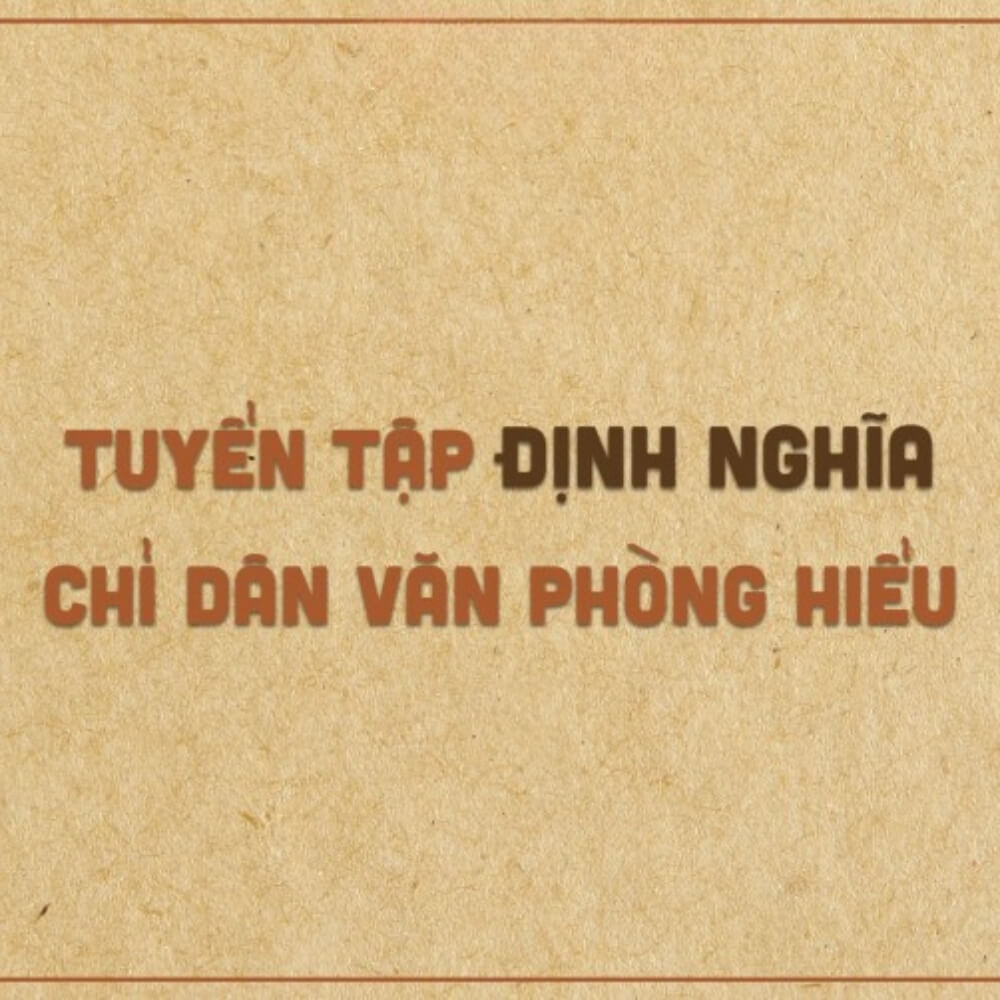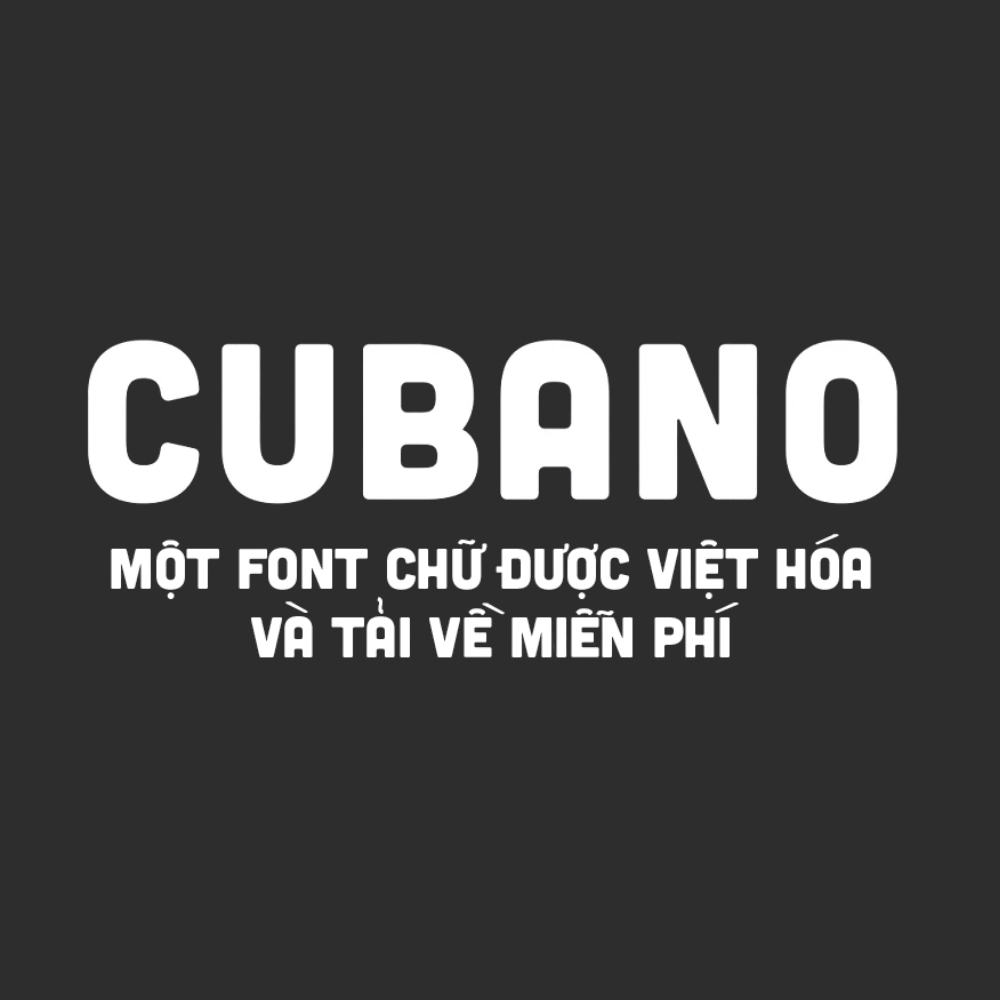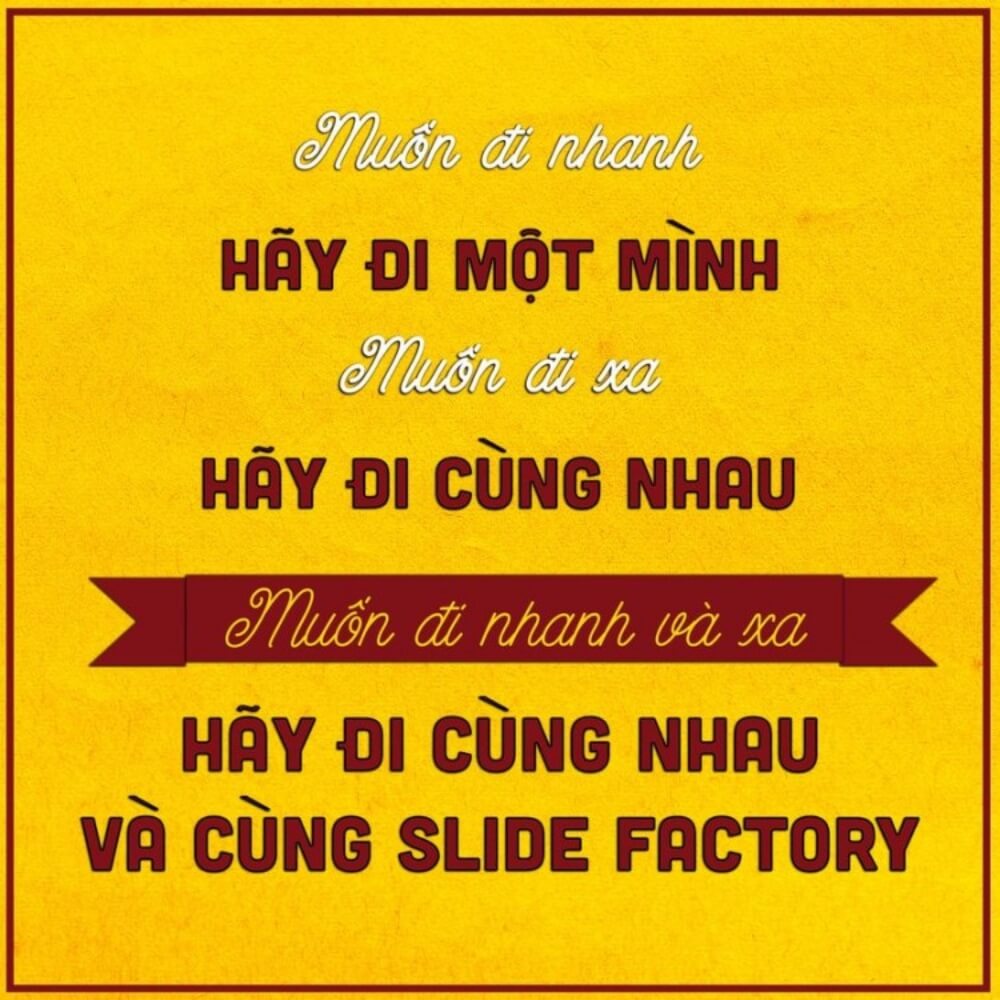
iCiel BC Cubano Normal là một trong những bộ font chữ thuộc dòng Sans-serif gây ấn tượng mạnh nhờ cấu trúc dày dặn, vững chãi kết hợp với các góc bo tròn đầy thân thiện. Với phong cách hiện đại và chuyên nghiệp, bộ font Việt hóa iCiel BC Cubano Normal đã trở thành công cụ hỗ trợ đắc lực cho các nhà thiết kế trong việc tạo ra những tiêu đề nổi bật và lôi cuốn.
Đặc trưng thẩm mỹ của bộ font Việt hóa iCiel BC Cubano Normal
Sức hút của font Cubano nằm ở sự cân bằng giữa sức mạnh và tính gần gũi. Các nét chữ được thiết kế với độ đậm cao, tạo cảm giác ổn định và đáng tin cậy, trong khi những đường bo góc giúp làm dịu đi sự thô cứng của các khối chữ lớn. Phiên bản font iciel cubano Việt hóa đã xử lý tinh tế hệ thống dấu tiếng Việt, giúp các ký tự đặc biệt giữ được sự đồng nhất về mặt hình học so với bản gốc, tránh hiện tượng lỗi dấu hoặc lệch tông khi trình bày văn bản.
Bên cạnh đó, iCiel BC Cubano Normal sở hữu khả năng hiển thị tốt trên nhiều nền tảng, từ các ấn phẩm in ấn khổ lớn đến giao diện kỹ thuật số. Cấu trúc chữ thông thoáng giúp người xem dễ dàng nhận diện thông tin ngay cả ở khoảng cách xa, điều này đặc biệt hữu ích cho các thiết kế bảng hiệu hoặc tiêu đề quan báo. Đây là phương án phù hợp để truyền tải những thông điệp mang tính khẳng định, chuyên nghiệp và đầy năng lượng.
| Phân loại phong cách | Sans-serif / Bold / Rounded |
| Đặc tính nổi bật | Nét dày, bo góc mềm mại, hiển thị rõ nét |
| Mục đích phù hợp | Tiêu đề, Poster, Logo, Bảng hiệu công trình |
Gợi ý thiết kế: Do iCiel BC Cubano Normal có độ đậm rất lớn, bạn nên sử dụng font này cho các tiêu đề chính hoặc các từ khóa cần tạo điểm nhấn mạnh mẽ. Việc phối hợp font này cùng một kiểu chữ Sans-serif mảnh và thoáng sẽ giúp bố cục thiết kế trở nên cân bằng và chuyên nghiệp hơn.
03 Ứng dụng font iciel cubano Việt hóa vào đời sống
Với vẻ ngoài hiện đại và vững chắc, bộ font chữ này mang lại giá trị thực tế cao khi được ứng dụng vào các hạng mục quảng bá và trang trí công trình:
- Bảng hiệu cho Văn phòng và Nhà lắp ghép: Những nét chữ dày của Cubano rất phù hợp để làm biển tên công ty, số nhà hoặc biển chỉ dẫn cho các khu văn phòng container, nhà lắp ghép hiện đại. Font chữ này giúp công trình toát lên vẻ chuyên nghiệp và chỉn chu.
- Thiết kế Poster và Truyền thông dự án: Sử dụng font icielbc Việt hóa cho các tiêu đề trên banner quảng cáo giúp thông tin trở nên tách bạch, dễ đọc và tạo được sự tin tưởng đối với khách hàng về quy mô và chất lượng dự án.
- Nhận diện thương hiệu cho dịch vụ vận tải và cơ khí: Cấu trúc mạnh mẽ của font Cubano rất ăn ý với các ngành nghề đòi hỏi sự bền bỉ, giúp logo và các ấn phẩm nhận diện của doanh nghiệp trông vững chãi và hiện đại.
03 Lưu ý kỹ thuật khi sử dụng font Việt hóa iCiel BC Cubano Normal
Để khai thác hiệu quả vẻ đẹp của dòng font đậm này mà không làm rối mắt người xem, người thiết kế nên lưu tâm một số kinh nghiệm sau:
- Kiểm soát khoảng cách ký tự: Do nét chữ của Cubano khá dày, đôi khi các ký tự có thể trông hơi sát nhau. Bạn nên điều chỉnh nới rộng khoảng cách một chút để chữ không bị bết dính, đặc biệt là khi hiển thị ở kích thước nhỏ.
- Hạn chế dùng cho đoạn văn bản dài: Độ đậm của font này không phù hợp để trình bày các nội dung thuyết minh hay hướng dẫn kỹ thuật dài vì sẽ gây mỏi mắt. Hãy để dành Cubano cho các vị trí tiêu đề hoặc slogan ngắn gọn.
- Lựa chọn màu sắc tương phản: Font chữ bold phát huy hiệu quả thị giác cao khi đặt trên các nền màu đơn sắc hoặc có độ tương phản rõ rệt, giúp các đường bo góc mềm mại của chữ được tôn vinh rõ ràng.